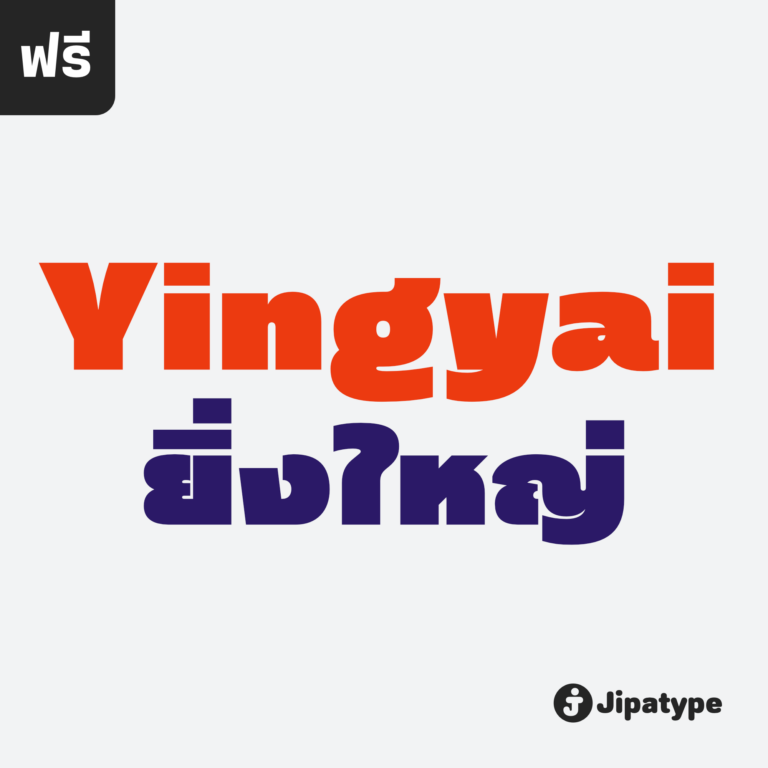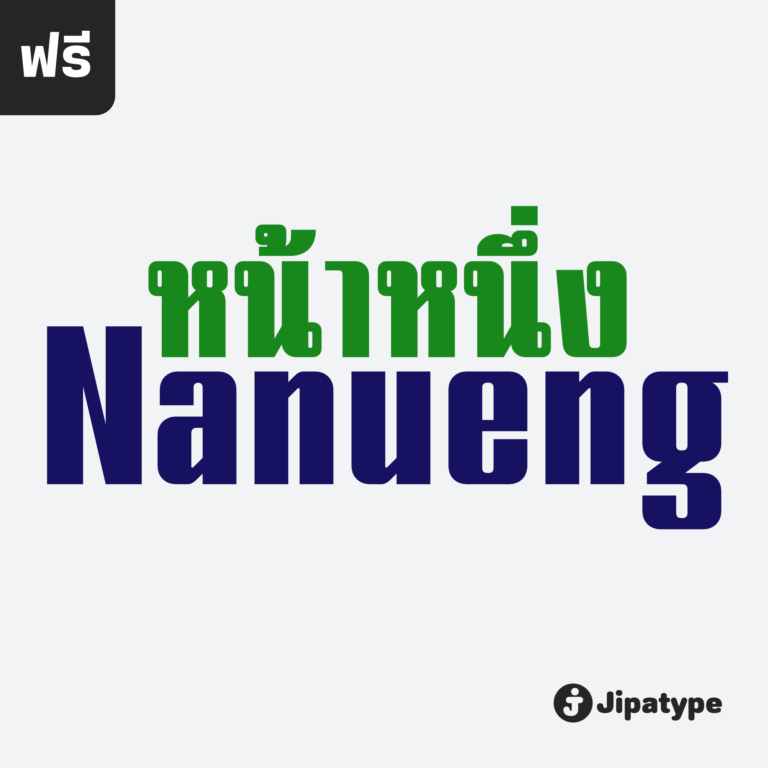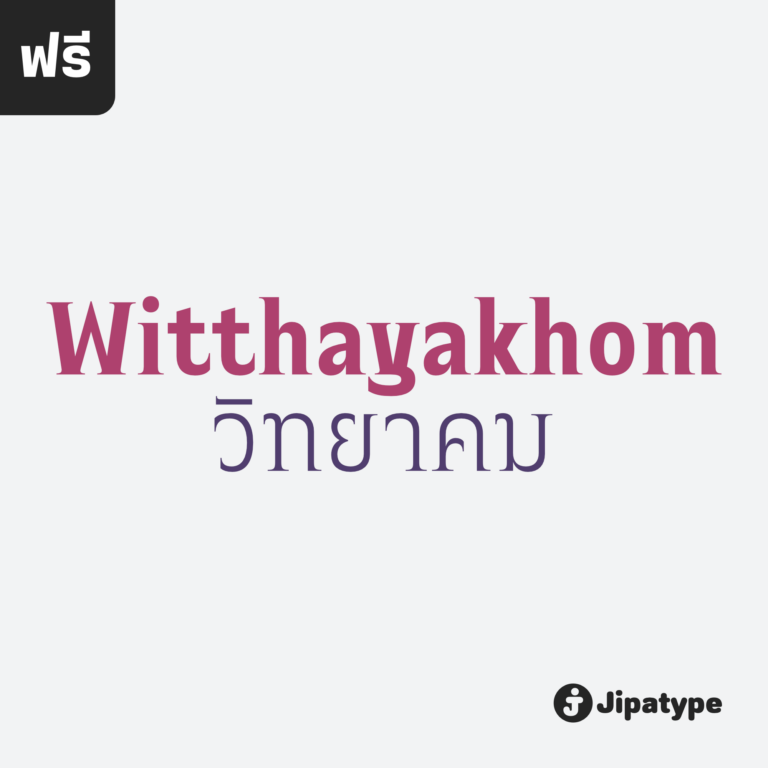
Jipatype
สร้างสรรค์ฟอนต์ไว้ทั้งหมด 116 ตัว
อบอุ่นลูป | Opun Loop
อบอุ่นลูป เป็นอักษรแบบแซนส์เซอริฟกลมมน มาพร้อมกับอักษรแบบมีหัวสำหรับภาษาไทย ดูกึงทางการ อ่อนโยน น่ารัก ใช้สำหรับเป็นพาดหัวก็ดี หรือเป็นเนื้อความก็เหมาะสม มีทั้งหมด 9 น้ำหนักและตัวเอียงของแต่ละน้ำหนักรวมทั้งหมดมี 18 สไตล์ และมีฟีเจอร์อื่น ๆ อาทิเช่น Small Caps และฟีเจอร์อื่น ๆ พร้อมให้คุณได้เลือกใช้งาน รองรับหลากหลายภาษา ออกแบบโดย : อานุภาพ ใจชำนาญ (Anupap Jaichumnan)สามารถใช้งานฟอนต์ได้ฟรีในเชิงพาณิชย์ ผ่านแอปฯ ของจิปาไทป์ ดูรายละเอียดและดาวน์โหลดแอปฯได้ที่ : jipatype.com
พัฒนา | Phatthana
ฟอนต์พัฒนา เป็นอักษรแบบพาดหัวแซนส์เซอริฟมีลักษณะโดยรวมเป็นทรงสี่เหลี่ยม ดูแข็งแกร่ง ทันสมัย ออกแนว ไซ-ไฟ ในโลกเทคโนโลยี เหมาะสำหรับการใช้พาดหัว รองพาดหัว มีทั้งหมด 9 น้ำหนักและตัวเอียงของแต่ละน้ำหนักรวมทั้งหมดมี 18 สไตล์ และมีฟีเจอร์อื่น ๆ เช่น Small Caps และฟีเจอร์อื่น ๆ พร้อมให้คุณได้เลือกใช้งาน รองรับหลากหลายภาษา ออกแบบโดย : อานุภาพ ใจชำนาญ (Anupap Jaichumnan)สามารถใช้งานฟอนต์ได้ฟรีในเชิงพาณิชย์ ผ่านแอปฯ ของจิปาไทป์ ดูรายละเอียดและดาวน์โหลดแอปฯได้ที่ : jipatype.com
หน้าหนึ่ง | Nanueng
ฟอนต์หน้าหนึ่ง เป็นอักษรแบบแซนเซอริฟที่แบบอักษรโดยรวมมีความเป็นสี่เหลี่ยม ซึ่งมีแบบอักษรจากหนังสือพิมพ์เป็นแรงบันดาลใจ ดูแข็งแกร่ง มีความเป็นเครื่องกล เครื่องจักรทันสมัย เหมาะสำหรับการใช้พาดหัว รองพาดหัว มีทั้งหมด 9 น้ำหนักและตัวเอียงของแต่ละน้ำหนัก รวมทั้งหมดมี 18 สไตล์ และมีฟีเจอร์อื่น ๆ เช่น Stylistic Set 01 และฟีเจอร์อื่น ๆ พร้อมให้คุณได้เลือกใช้งาน รองรับหลากหลายภาษา ออกแบบโดย : อานุภาพ ใจชำนาญ (Anupap Jaichumnan)สามารถใช้งานฟอนต์ได้ฟรีในเชิงพาณิชย์ ผ่านแอปฯ ของจิปาไทป์ ดูรายละเอียดและดาวน์โหลดแอปฯได้ที่ : jipatype.com
ยิ่งใหญ่ | Yingyai
ฟอนต์ยิ่งใหญ่ เป็นอักษรแบบแซนเซอริฟ ที่มีความหนาของเส้นมากว่าปกติ สังเกตได้จากน้ำหนัก Black ให้ความรู้สึกหนักแน่น หนา ใหญ่ และ ทันสมัย มีทั้งหมด 9 น้ำหนักและตัวเอียงของแต่ละน้ำหนักรวมทั้งหมดมี 18 สไตล์ รองรับหลากหลายภาษา เหมาะสำหรับการใช้พาดหัว ป้าย เนื้อความ ฟอนต์ยิ่งใหญ่สามารถช่วยส่งเสริมให้งานของคุณดูสะดุดตาอย่างยิ่ง เหมาะกับผู้ที่ต้องการให้โฆษณาสินค้าและบริการดูสะดุดตากว่าใคร ๆ ออกแบบโดย : อานุภาพ ใจชำนาญ (Anupap Jaichumnan)สามารถใช้งานฟอนต์ได้ฟรีในเชิงพาณิชย์ ผ่านแอปฯ ของจิปาไทป์ ดูรายละเอียดและดาวน์โหลดแอปฯได้ที่ : jipatype.com
อุตสาหกรรม | Utsahakam
ฟอนต์อุตสาหกรรม เป็นอักษรแบบสลับเซอริฟ ที่มีความแข็งแกร่ง หนักแน่น มั่นคง มีทั้งหมด 9 น้ำหนักและตัวเอียงของแต่ละน้ำหนักรวมทั้งหมดมี 18 สไตล์ รองรับหลากหลายภาษาและได้ขยายการรองรับภาษาเวียดนามเพิ่ม เหมาะสำหรับการใช้พาดหัว ป้าย ข้อความโปรยสั้นๆ ฟอนต์อุตสาหกรรมสามารถช่วยส่งเสริมมู้ดแอนด์โทนให้ดูหนักแน่น มั่นคง น่าเชื่อถือ เหมาะกับสินค้าและบริการที่เกี่ยวข้องกับ เครื่องจักร, โรงงานการผลิต, เครื่องมือช่าง หรืออุตสาหกรรมหนัก ออกแบบโดย : อานุภาพ ใจชำนาญ (Anupap Jaichumnan)สามารถใช้งานฟอนต์ได้ฟรีในเชิงพาณิชย์ ผ่านแอปฯ ของจิปาไทป์ ดูรายละเอียดและดาวน์โหลดแอปฯได้ที่ : jipatype.com
ปุยปุย | Puipui
ฟอนต์ปุยปุย เป็นอักษรแบบแซนเซอริฟที่มีความมน มีคอนทราสต์ของเส้น ดูเรียบง่าย มีทั้งหมด 9 น้ำหนักและตัวเอียงของแต่ละน้ำหนักรวมทั้งหมดมี 18 สไตล์ รองรับหลายภาษาและภาษาไทย เหมาะสำหรับการใช้พาดหัวหรือตัวเนื้อความ ฟอนต์ปุยปุยสามารถช่วยส่งเสริมมู้ดแอนด์โทนให้ดูน่ารักยิ่งขึ้น เหมาะกับสินค้าที่เกี่ยวข้องกับเด็ก, สัตว์เลี้ยง, อาหาร หรือคอนเทนต์ที่ต้องการความน่ารัก ออกแบบโดย : อานุภาพ ใจชำนาญ (Anupap Jaichumnan)สามารถใช้งานฟอนต์ได้ฟรีในเชิงพาณิชย์ ผ่านแอปฯ ของจิปาไทป์ ดูรายละเอียดและดาวน์โหลดแอปฯได้ที่ : jipatype.com
กรุบกรอบ | Krupkrop
ฟอนต์ กรุบกรอบ แบบอักษรที่ใช้เส้นตรงเป็นหลักในการออกแบบโครงสร้างอักษร มีการเอียงเส้นแนวตั้ง (Stem) เล็กน้อย ให้ความรู้สึก ไม่เป็นทางการ แข็งกรอบ สนุกสนาน มีชีวิตชีวา ไม่หยุดนิ่ง เหมาะกับผาดหัวบนสื่อต่างๆ เช่น ป้ายโฆษณา แพ็คเกจมีทั้งหมด 9 น้ำหนัก และตัวเอียงของแต่ละน้ำหนัก รวม 18 สไตล์ ออกแบบโดย : อานุภาพ ใจชำนาญ (Anupap Jaichumnan)สามารถใช้งานฟอนต์ได้ฟรีในเชิงพาณิชย์ ผ่านแอปฯ ของจิปาไทป์ ดูรายละเอียดและดาวน์โหลดแอปฯได้ที่ : jipatype.com
นมัสการ | Namaskarn
ฟอนต์ นมัสการ แบบอักษรได้แรงบันดาลใจจากเขียนตัวอักษรวิจิตรด้วยปากกาหัวตัด ที่มีองศาในการเดินเส้นที่ 45 องศา เลยเอาตัวเลข 45 องศามาใช้ในการออกแบบ สังเกตได้จากการจบเส้น เช่น c, r ปลายตัดที่ 45 องศา  แบบอักษรมีความเปรียบต่างสูง เหมาะกับการใช้เป็นพาดหัว ข้อความสั้นๆ หรือ Quote มี 9 น้ำหนัก ทั้งตัวตรงและตัวเอียงรวมเป็น 18 สไตล์ ที่ใช้ชื่อ นมัสการ เพราะว่าตัวอักษรที่ใช้ปากกาสปีดบอลหรือปลายตัดพบเห็นได้บ่อยตามวัดวาอารามต่าง ๆ ออกแบบโดย : อานุภาพ ใจชำนาญ (Anupap Jaichumnan)สามารถใช้งานฟอนต์ได้ฟรีในเชิงพาณิชย์ ผ่านแอปฯ ของจิปาไทป์ ดูรายละเอียดและดาวน์โหลดแอปฯได้ที่ : jipatype.com
หาดทราย | Hadsai
ฟอนต์ หาดทราย ลักษณะกลมมน เส้น Stem มีความหนาแตกต่างกันสองขนาด หนา-บาง ไม่เท่ากัน การเดินเส้นเลียนแบบลายมือ มาพร้อมกับฟีเจอร์ dlig ที่เปิดใช้งานแล้วจะยกตัวอักษรลำดับที่สองให้สูงขึ้นเล็กน้อยสลับกันเป็นฟันปลา เหมือนคลื่นเล็ก ๆ บนผิวน้ำให้ความรู้สึกเป็นมิตร น่ารักใสๆ มีไดนามิก สนุกสนาน ไม่เป็นทางการ เหมาะสำหรับการพาดหัว โปรยประโยคข้อความสั้น ๆมีให้เลือกใช้ 9 น้ำหนัก ทั้งตัวตรงและตัวเอียงรวมเป็น 18 สไตล์ ออกแบบโดย : อานุภาพ ใจชำนาญ (Anupap Jaichumnan)สามารถใช้งานฟอนต์ได้ฟรีในเชิงพาณิชย์ ผ่านแอปฯ ของจิปาไทป์ ดูรายละเอียดและดาวน์โหลดแอปฯได้ที่ : jipatype.com
วันวาน | Wanwan
ฟอนต์ วันวาน อักษรแบบตัวเขียนอ้างอิงจากสไตล์การเขียนแบบพู่กันให้ความรู้สึกพลิ้วไหว มีสไตล์ให้เลือกใช้ 9 สไตล์ เป็นตัวเอียงทั้งหมด
บรรทัด | Bantat
ฟอนต์ Bantat เป็นแบบอักษร Sans Serif ที่มีความเรียบง่ายโดยออกแบบให้หลังคาและฐานตัวอักษรกลุ่มหนึ่งราบเรียบไปกับเส้นบรรทัด ผสมกับหลังคาแบบปกติ เพื่อให้มี Dynamic แทนที่จะราบเรียบไปทุกตัวอักษร ฟอนต์ Bantat เหมาะสำหรับงานทั่วไป บนสื่อได้หลากหลายขนาดไม่ว่าจะมีความกว้างหรือแคบ ออกแบบโดย : อานุภาพ ใจชำนาญ (Anupap Jaichumnan)สามารถใช้งานฟอนต์ได้ฟรีในเชิงพาณิชย์ ผ่านแอปฯ ของจิปาไทป์ ดูรายละเอียดและดาวน์โหลดแอปฯได้ที่ : jipatype.com
ระหง | Rahong
แบบอักษรผอมแคบ คงค่าพื้นที่ภายในอักษรให้เท่ากัน(เกือบ)ทุกตัว ทำให้ดูสูงกว่าปกติเหมาะกับมีเดียที่ต้องใช้พื้นที่จำกัด ถ้าใช้เป็นผ่าดหัวช่วยสร้างความสนใจได้เป็นอย่างดี ออกแบบโดย : อานุภาพ ใจชำนาญ (Anupap Jaichumnan)สามารถใช้งานฟอนต์ได้ฟรีในเชิงพาณิชย์ ผ่านแอปฯ ของจิปาไทป์ ดูรายละเอียดและดาวน์โหลดแอปฯได้ที่ : jipatype.com